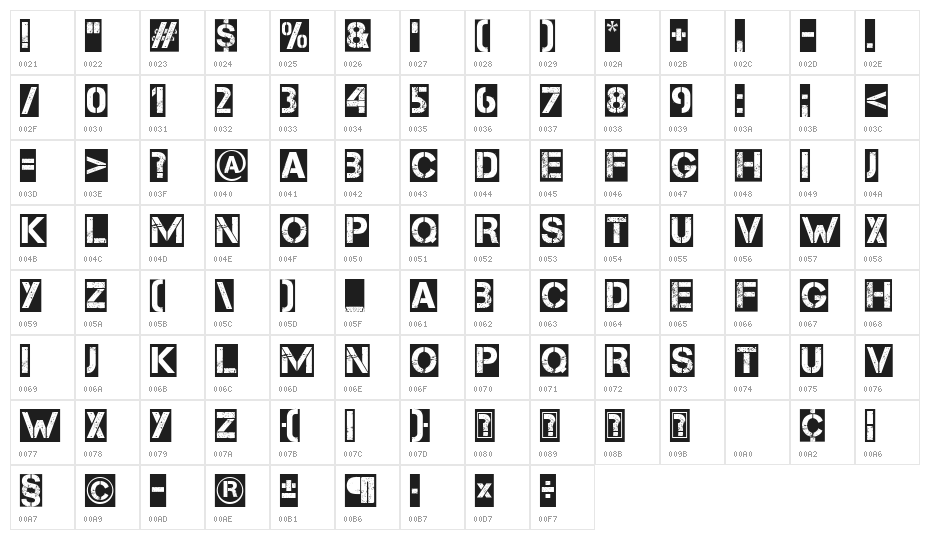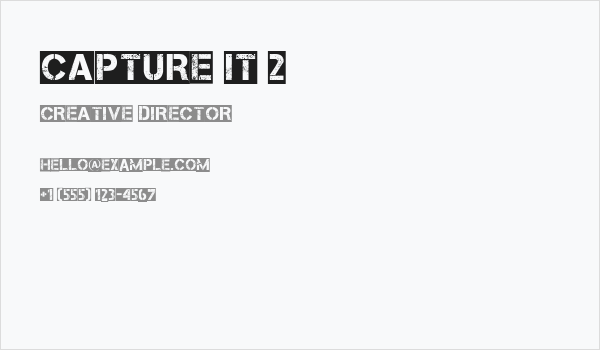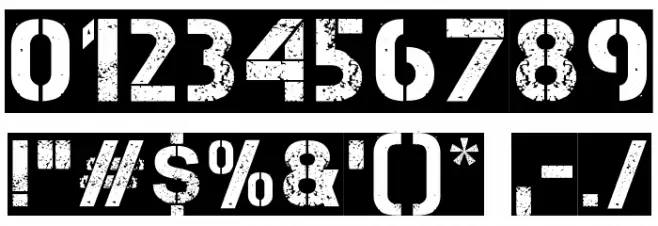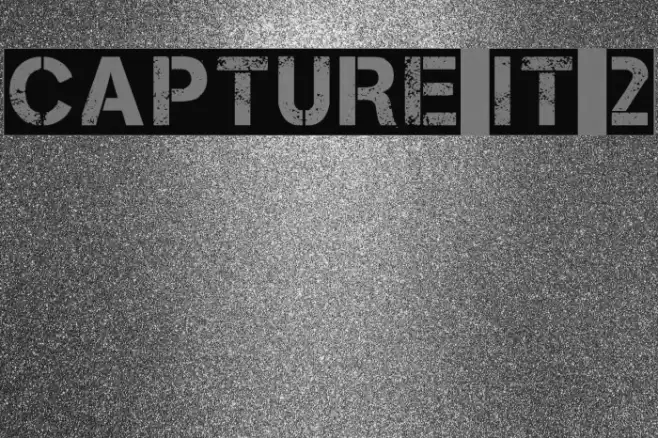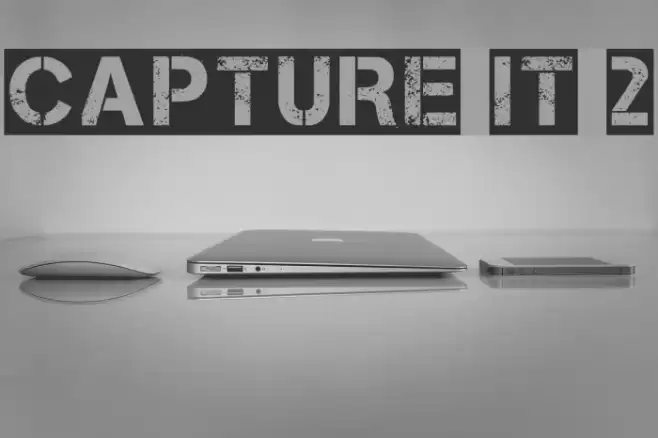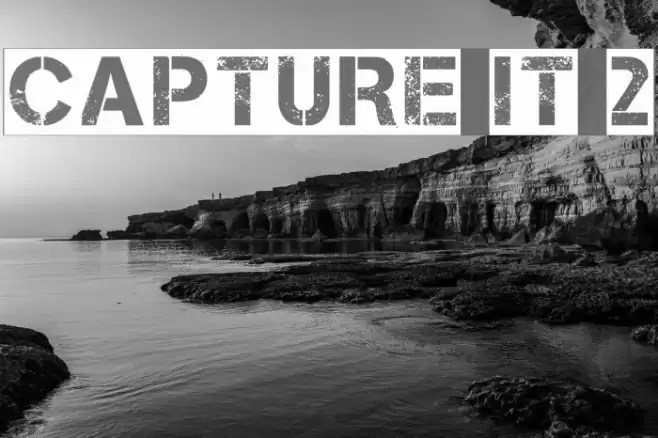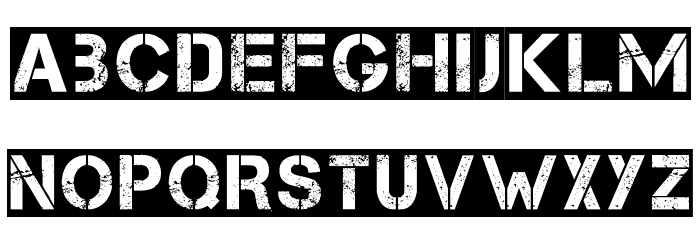
Capture it 2 Font
| Estilo general | Vintage, Industrial |
| Proyectos propuestos | Ideal for posters, album covers, branding for edgy or industrial-themed products, and any design requiring a strong, impactful visual statement. |